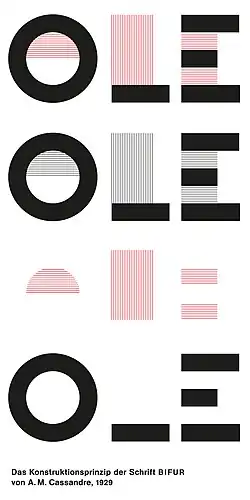
Bifur (Schriftart)
Schriftart Bifur
Kategorie Akzidenzschrift
Schriftklassifikation Serifenlose Linear-Antiqua (DIN 16518)
Schriftdesigner A. M. Cassandre
Auftraggeber Charles Peignot
Schriftgießerei Deberny & Peignot
Erstellung 1929
Wiederveröffentl. 2004
Inhaber Linotype
Variationen P22 Bifur A - F
Bifur wurde 1929 von dem französischen Plakatkünstler und Typografen A. M. Cassandre für die Schriftgießerei Deberny & Peignot entworfen.[1] Seit Ende 1927 arbeitete er an ihrer Entwicklung. Als Plakatgestalter betrachtete Cassandre den Buchstaben und die Schrift nicht nur als Informationsträger, sondern gleichrangig zur Bildidee als grafische Form. Er fasste den Buchstaben nicht mehr als eine lineare Form auf, sondern als Fläche. Die Schrift wurde so zum Spielfeld für Farb- und Weissräume.
Bifur ist eine der eindrucksvollsten Akzidenzschriften der Art déco Ära. Sie wurde für die Werbung geschaffen und sollte sich in erster Linie im Gedächtnis der Betrachter einprägen. Cassandre vereinfachte den Aufbau der Buchstaben, verstärkte den geometrischen Aspekt ihrer Formen und schraffierte einzelne Flächen der Buchstaben oder ihre Punzen. Die flächigen, geometrischen Buchstabenformen und die schraffierten Flächen waren als zweiteilige Lettern (auf zwei getrennten Kegeln) angelegt, so konnte die Bifur in zwei Farben gedruckt werden. Bifur ist durch die fetten und dünnen Linien und Querbalken eine sehr auffällig gestaltete Schrift des Art déco.[2][3]
2004 wurde Bifur von Richard Kegler in sechs Schriftschnitten bei International House of Fonts (IHOF) neu herausgebracht.[4]
Zitat
Das Konstruktionsprinzip der Schrift BIFUR als zweigeteilte Letter von Cassandre
In der Zeitschrift Arts et Métiers graphiques Nr. 9 stellte Cassandre seine Bifur-Schrift vor und schrieb unter anderem über sie:
„Vorsicht! Bifur wurde wie ein Eisenbahnsignal entworfen, damit sie funktioniert – Vollbremsung. Wenn sie aus Versehen, aufgrund des Fehlers eines ungeschickten Typographen nicht funktioniert – dann ist die Katastrophe unausweichlich. Bifur ist als Werbeschrift entworfen worden, um ein Wort, ein einziges Wort, ein Plakatwort zu drucken.“[5]